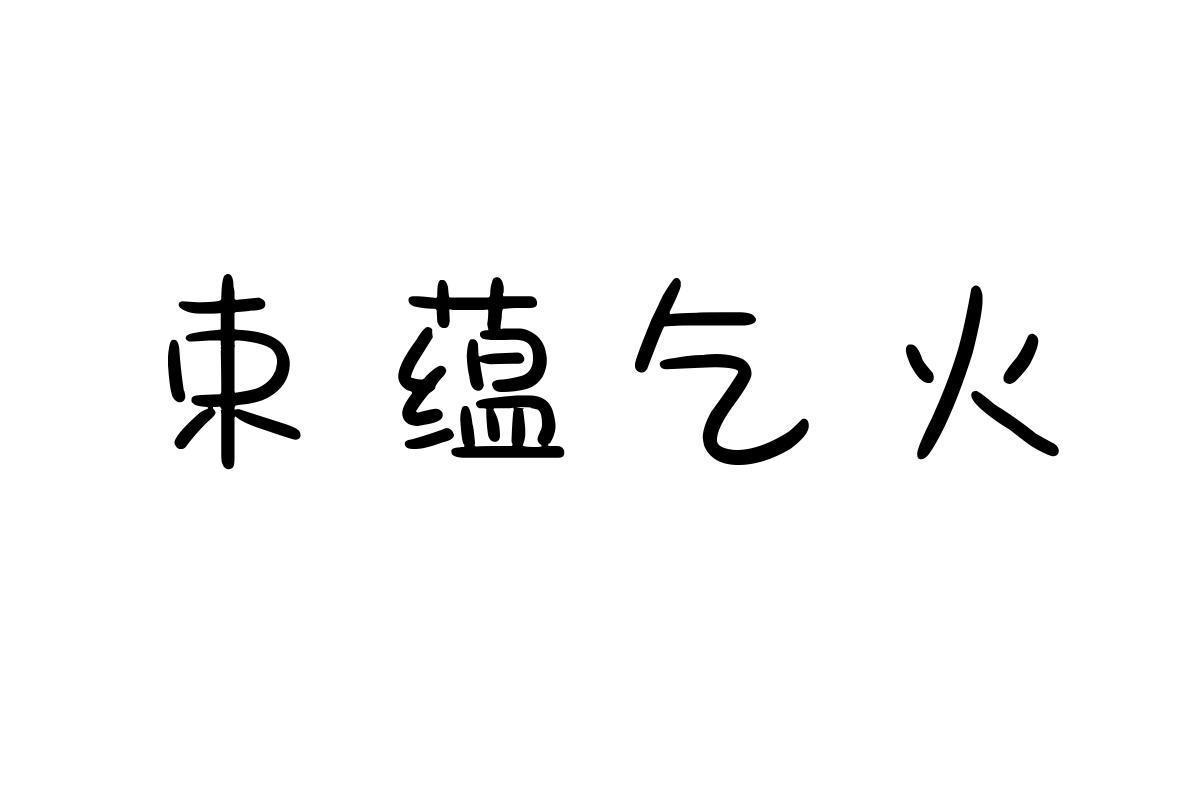
也字工厂软萌欧包体字体是一种可爱且具有亲和力的手写字体,适用于需要表达温柔、亲切和可爱的设计场景。这种字体的特点是线条柔和,字形圆润,给人一种温馨的感觉。它的笔画流畅,结构紧凑,适合用于儿童插画、卡通形象、贺卡设计等需要传达温暖和爱意的场合。也字工厂软萌欧包体字体的笔画粗细适中,既有力度又不失柔和,能够很好地与文字内容相融合,增强整体设计的美感和吸引力。